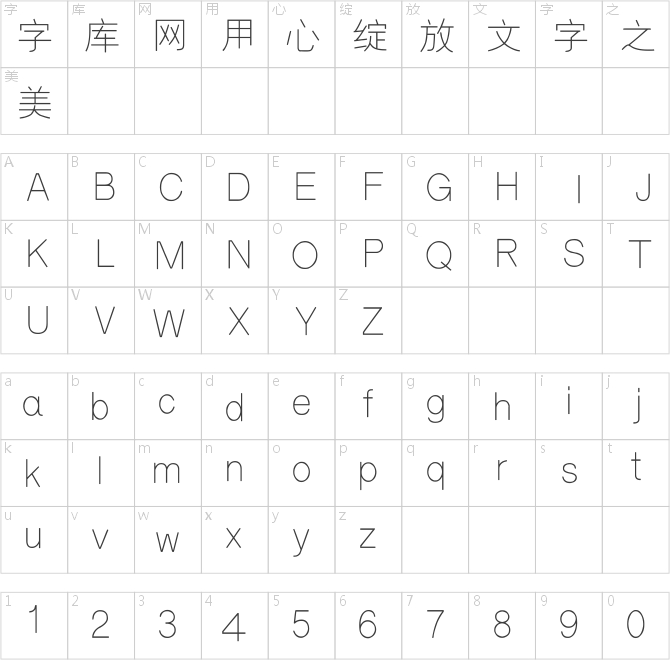
漢標(biāo)細(xì)黑體
黑體
細(xì)的
漢標(biāo)細(xì)黑體字體字庫是一款讓人賞心悅目、百看不厭的中文字體,適合各類廣告和產(chǎn)品包裝設(shè)計應(yīng)用,字體大小2.33MB,格式為ttf字體,上傳用戶是漢標(biāo)文創(chuàng),作者/版權(quán)方為漢標(biāo)字庫